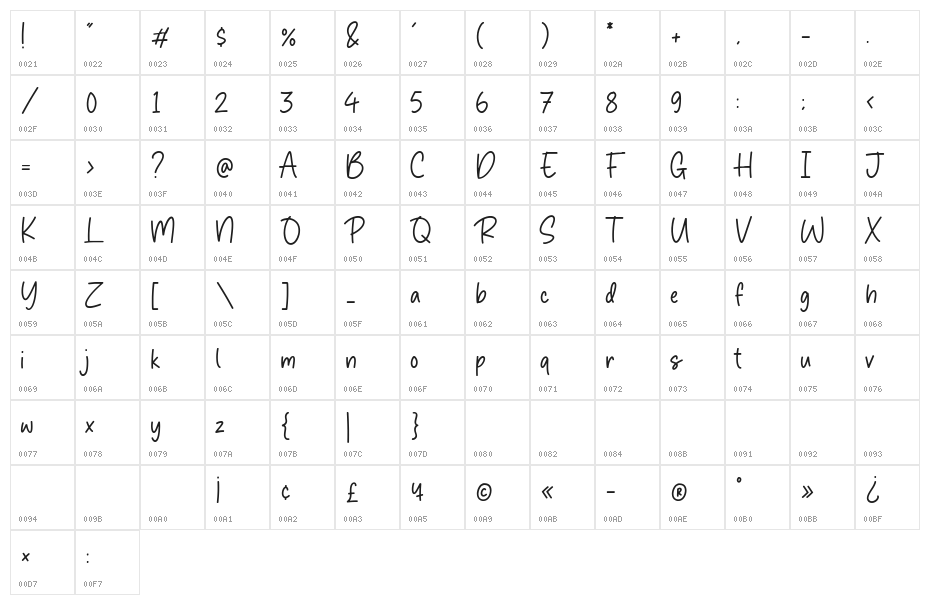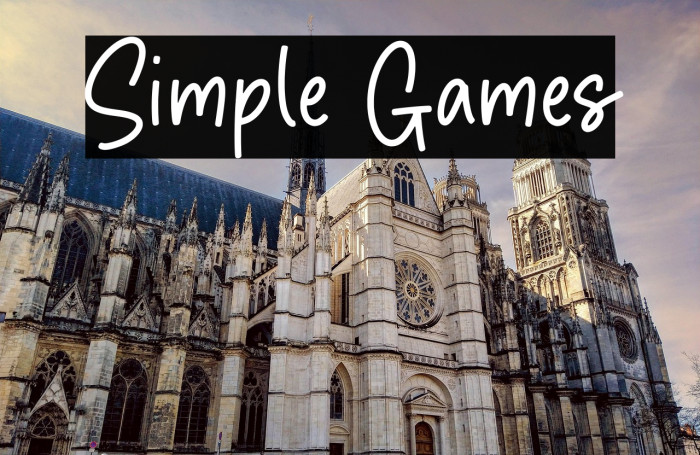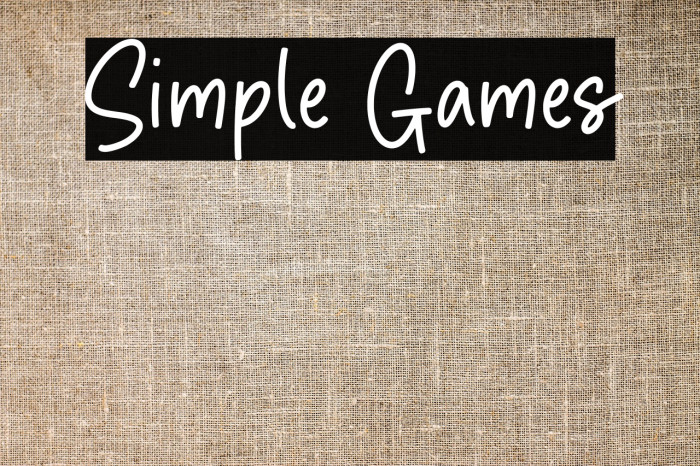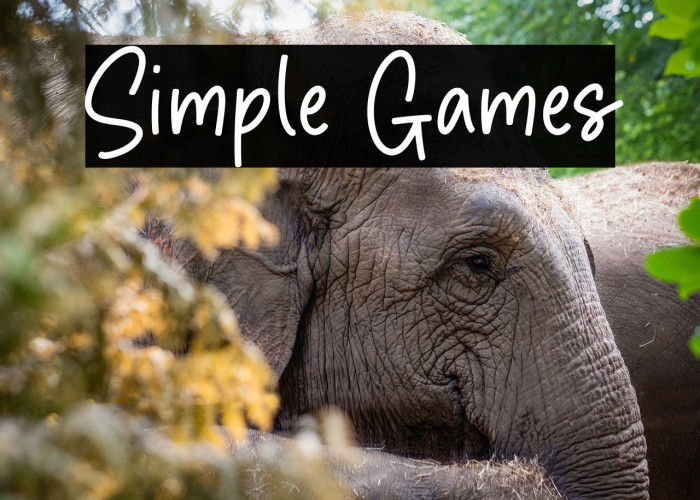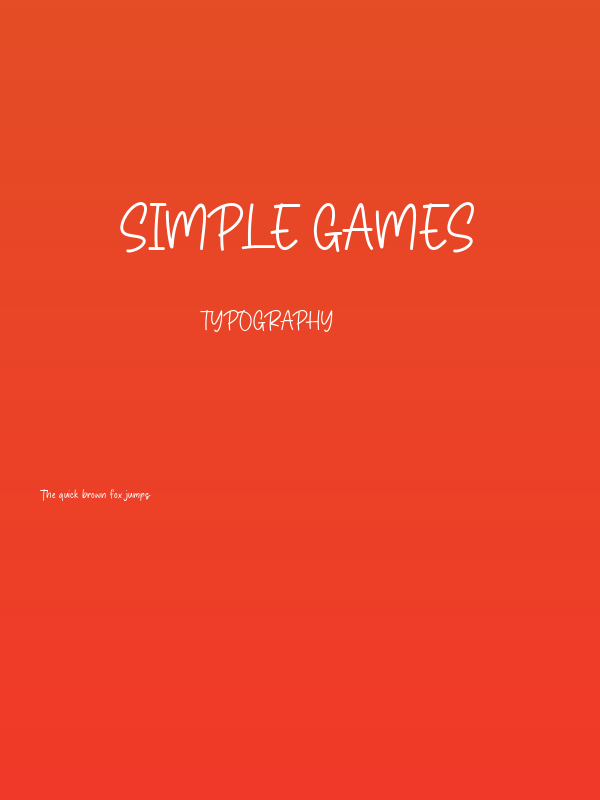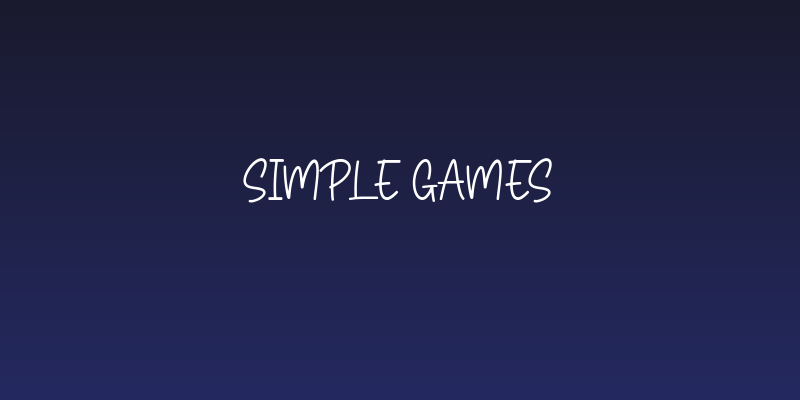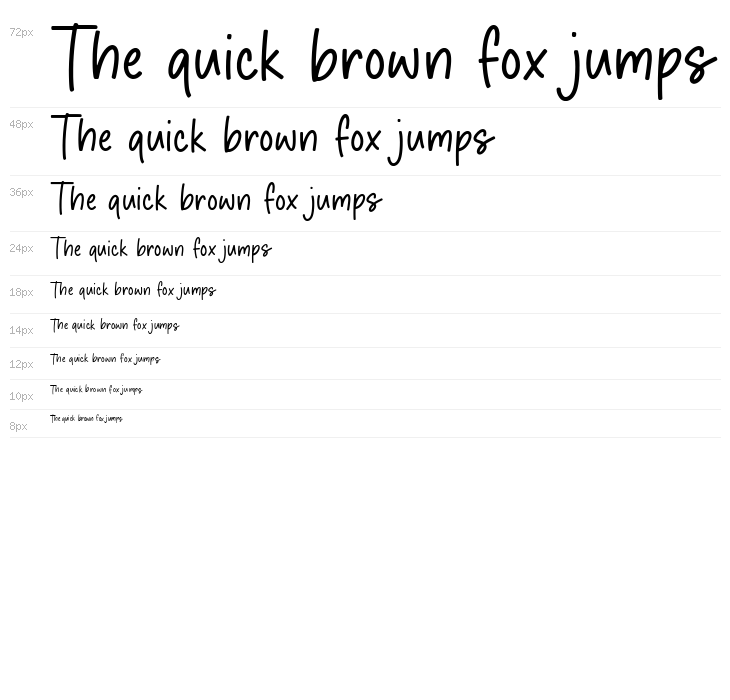
Simple Games Font
| Stile generale | Playful, Casual, Friendly |
| Caso d'uso | Headlines, Posters, Informal notes, Children’s content |
| Progetti proposti | Children’s books, educational materials, greeting cards, informal branding, playful posters. |